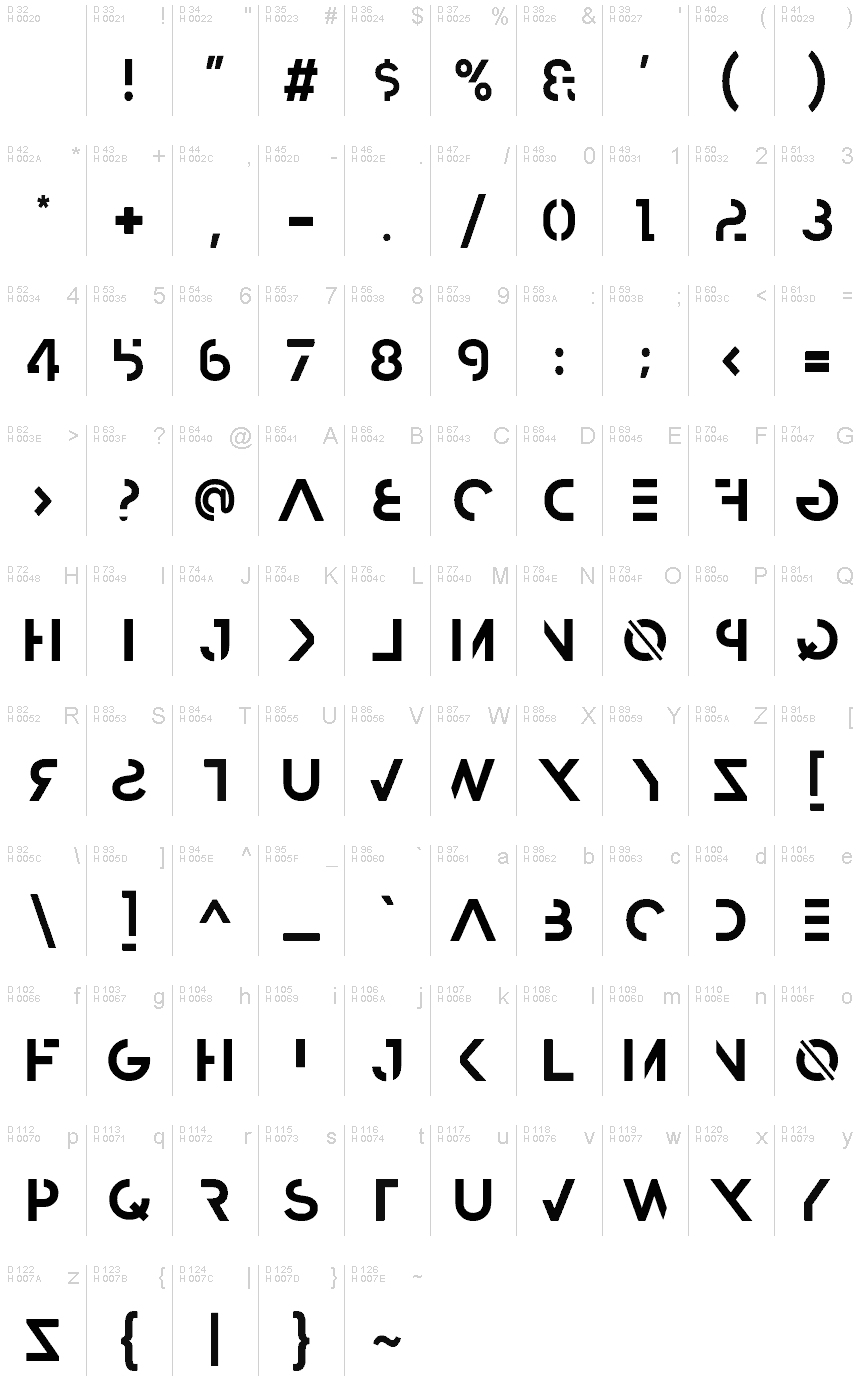
Razed Bold
Il font Razed (pronunciato "raised") prende il nome da "erased" (cancellato), richiamando il suo design minimalista. Se "raised" suggerisce intensità, forza o elevazione, Razed punta all'essenziale. Un carattere moderno e contemporaneo per il graphic design!
HBM Razed - A modern scifi font.